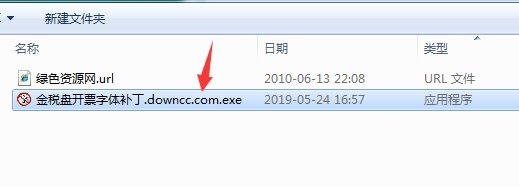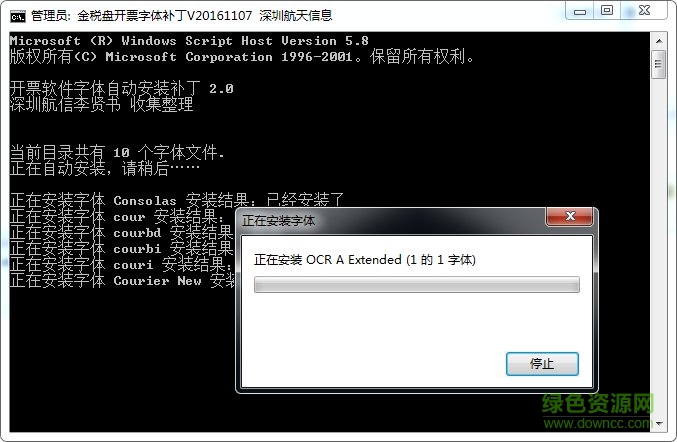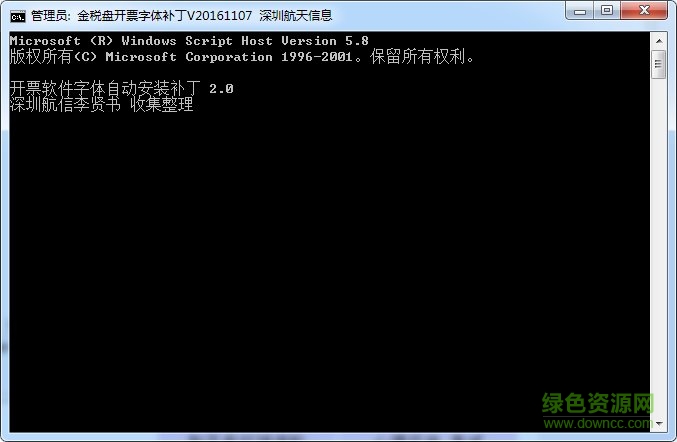
金稅盤開票字體補(bǔ)丁是一款可以幫助修改打印字體的工具。該字體樣式優(yōu)美、字跡清晰,可以讓您在打印文本的時(shí)候提高文字質(zhì)量,安裝航天信息無法打印,當(dāng)前操作系統(tǒng)缺少ocr a extended等字體樓主:驅(qū)動(dòng)沒有正確安裝,卸載后再安裝,如果還是不能安裝的話就換一個(gè)對(duì)應(yīng)的驅(qū)動(dòng)。如果還是不行,那么系統(tǒng)可能有問題了。
1、提供豐富的文字編輯方式,一鍵選取您需要修改的文字部分就可以了
2、金稅盤字體其實(shí)有三種字體,支持標(biāo)準(zhǔn)黑體、簡體、微軟繁綜藝
3、可以在打印的時(shí)候選擇win系統(tǒng)發(fā)的字體做為打印字體輸出